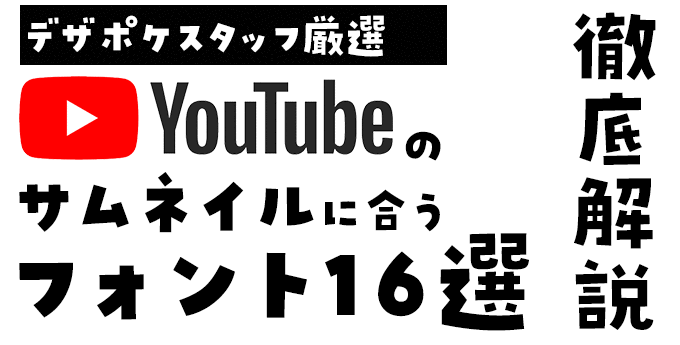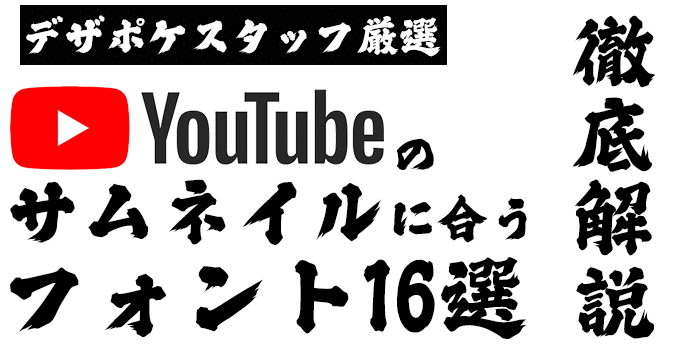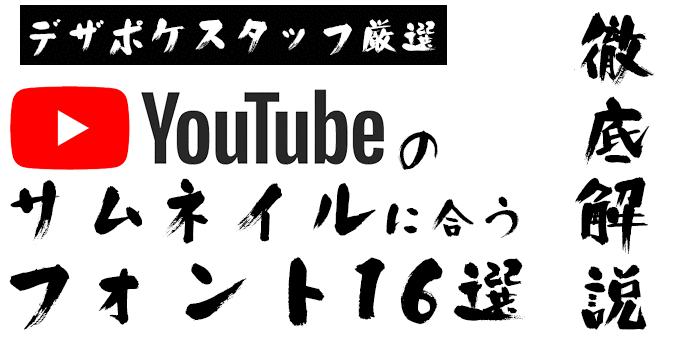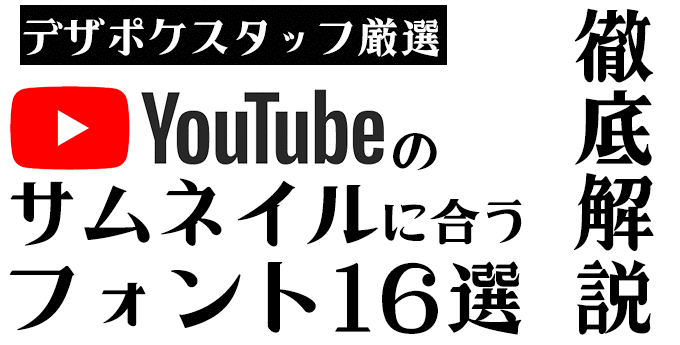
YouTubeのサムネイルに合うフォント 特化型 目的別フォントガイド
使用フォント:DSあかり
YouTubeのサムネイルに合うフォント:特化型 目的別フォントガイド #025
今回はYouTubeのサムネイルに合うフォント。日々フォントのことばかり考えている当店スタッフが直感的に選んだフォントをご紹介します。
YouTubeのサムネイルに合うフォントをスタッフが選びました
YouTubeのサムネイルに合うフォント #1 パンダベーカリー
パンダベーカリー【鈴木メモ】
『パンダベーカリー』は角ばったかわいらしい字体が特徴的なフォントで、サムネイルにもにも最適なしっかりとした太さです。
YouTubeのサムネイルに合うフォント #2 期間限定!鬼滅のフォント3書体セット
期間限定!鬼滅のフォント3書体セット【昭和書体/コーエーサインワークス】
有名アニメの人物紹介で使用された期間限定販売の毛筆書体セット。YouTubeのサムネイルやテロップ、TV番組でも使用される人気の書体です。※上記サンプルは【黒龍】で作成しております。
YouTubeのサムネイルに合うフォント #3 JTCじゃんけんU
JTCじゃんけんU【ニィスフォント】
コミカル、かわいい印象ながらもしっかりした太さがあり、笑いのある場面のテロップに使いたい書体。
YouTubeのサムネイルに合うフォント #4 花とちょうちょ
花とちょうちょ【鈴木メモ】
YouTubeだけでなく、インスタグラムなどのSNSでたくさんの方に使用されている手書き書体。MV、ライフログ、料理・レシピ、美容系など様々なジャンルの動画サムネでメッセージ性を高めてくれるフォントです。
YouTubeのサムネイルに合うフォント #5 バサころ(恵彩院花梢 3書体セット)
バサころ(恵彩院花梢 3書体セット)【昭和書体/コーエーサインワークス】
かすれのある極太筆文字で目を引きます。英数字の表記にも違和感がないので多用途に使えます。今なら同作家の細目筆文字もセットでお買い得!※上記サンプルは【KSWバサころ】で作成しております。
YouTubeのサムネイルに合うフォント #6 昭和ひげ文字
昭和ひげ文字【昭和書体/コーエーサインワークス】
「とめ」「はね」「はらい」にひげが生えたおもしろい筆文字。太さもありインパクト大の書体です。
YouTubeのサムネイルに合うフォント #7 喜縁体
喜縁体【楽フォント】
極太ロゴタイプで跳ね上がるリズミカルなデザインが目を引きます。同ブランドの全書体を利用できる『年間ライセンス』のご購入をオススメします!
YouTubeのサムネイルに合うフォント #8 横丁&鍛所 ファイトフォント
横丁&鍛所 ファイトフォント【六葉情報】
勢いのあるはらいが特徴的な極太の毛筆書体で、荒々しく力強い印象を持っています。インパクトのあるサムネイルにもピッタリのフォントです。
YouTubeのサムネイルに合うフォント #9 デザイン筆文字フォント酔虎
デザイン筆文字フォント酔虎【マール社】
有名ローカル深夜番組をはじめ数多くのTV番組やゲームでも使用される荒々しい毛筆書体。強めのメッセージを伝えたいときのサムネに最適なフォントです。
YouTubeのサムネイルに合うフォント #10 はちまるポップ
はちまるポップ【かに沢のりお】
1970から80年代に流行した、丸文字をイメージしたファンシーで丸っこいフォント。子供向けの動画やかわいいもの紹介などのサムネイルに最適なフォントです。
YouTubeのサムネイルに合うフォント #11 虹みんちょう
虹みんちょう【かに沢のりお】
少しレトロな雰囲気の手作りの明朝体フォント。太さもあるのでサムネサイズでも読みやすく優しい印象に仕上がるフォントです。
YouTubeのサムネイルに合うフォント #12 レトロゲームっぽいフォント AFSゴシック10■R
レトロゲームっぽいフォント AFSゴシック10■R【フォントユーコム】
レトロのゲームの雰囲気を醸し出すアウトラインフォント。ゲーム関連の動画サムネに最適なフォントです。
YouTubeのサムネイルに合うフォント #13 g_コミックホラー恐怖(R)
g_コミックホラー恐怖(R)【よく訓練されたフォント屋】
ホラーシーンのセリフに使用する事を想定して作成したホラーフォント。恐怖系の動画サムネに最適なフォントです。